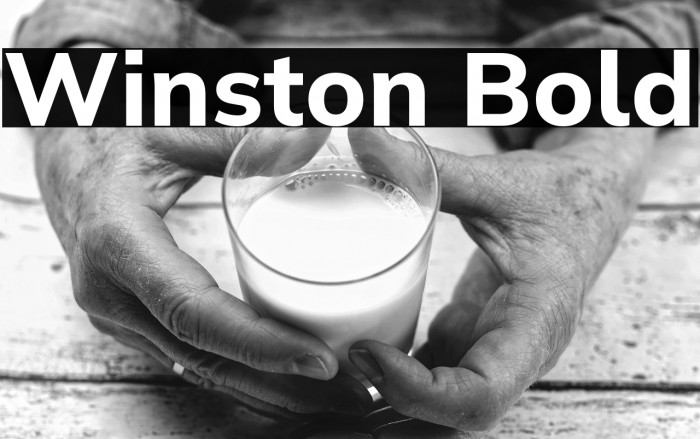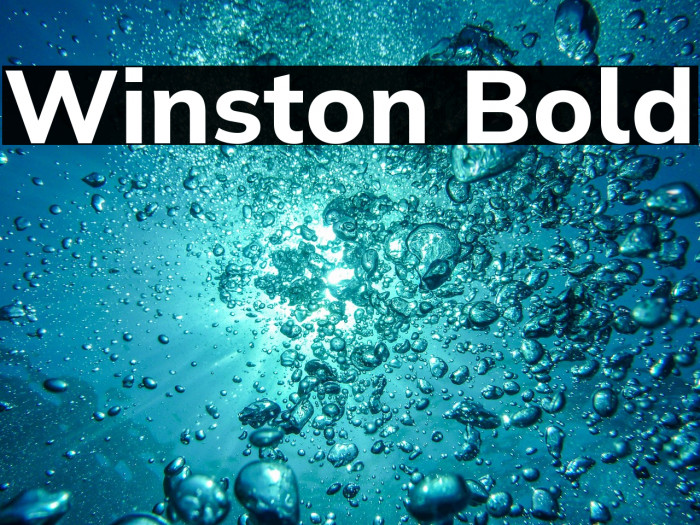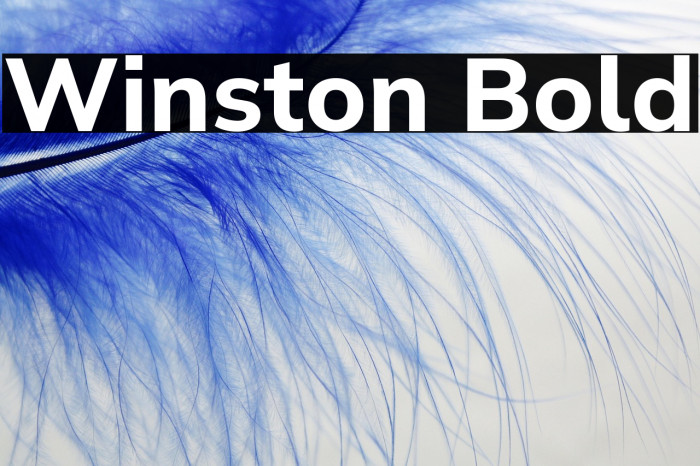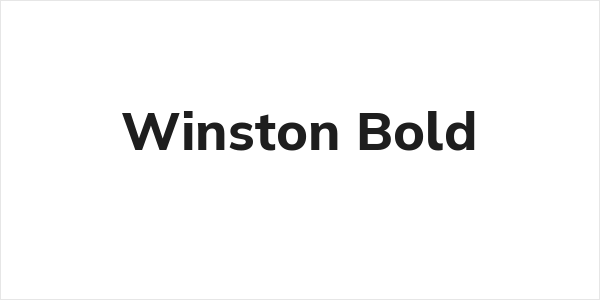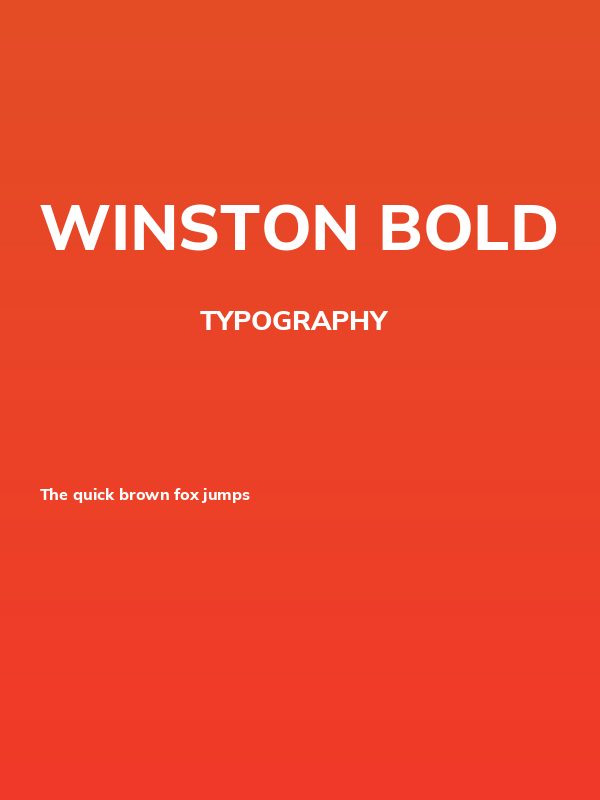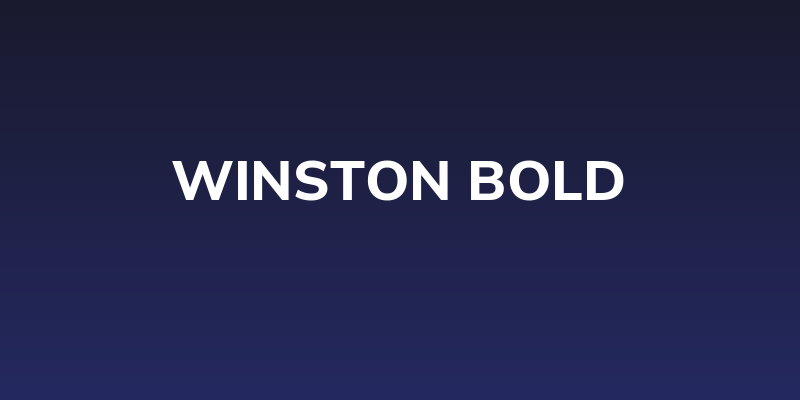
Winston Bold Font
| Caso d'uso | Headlines, Logos, Branding |
| Progetti proposti | Ideal for branding, headlines, advertising, and digital media where a strong, modern presence is desired. |